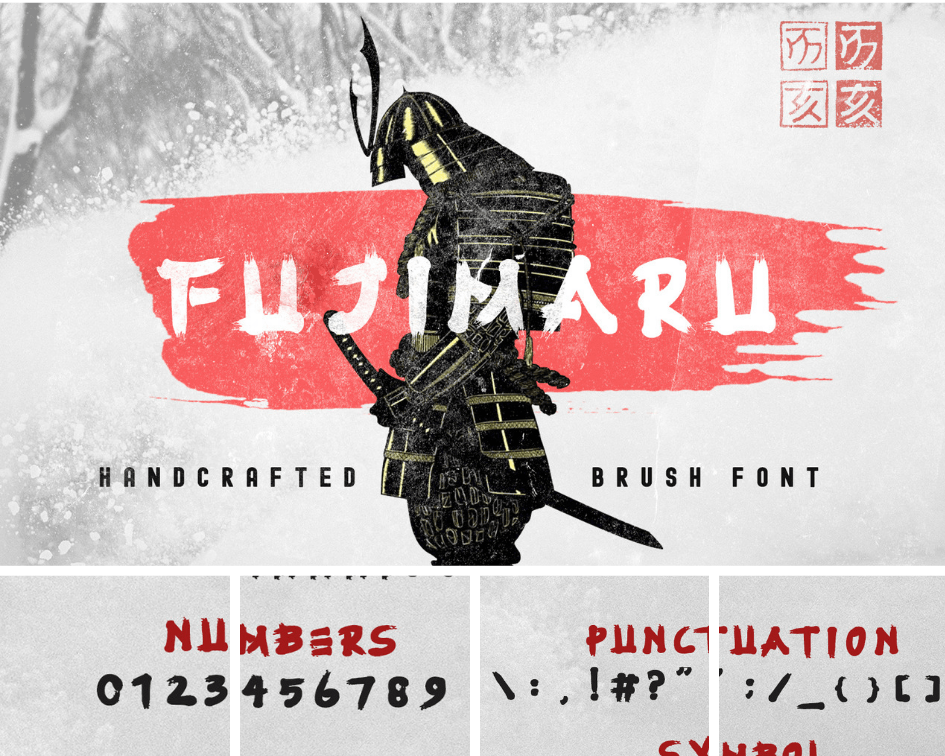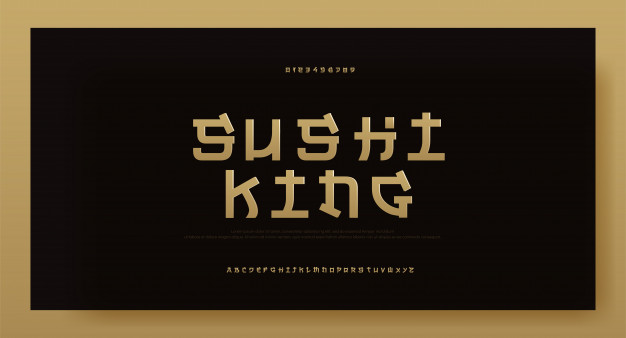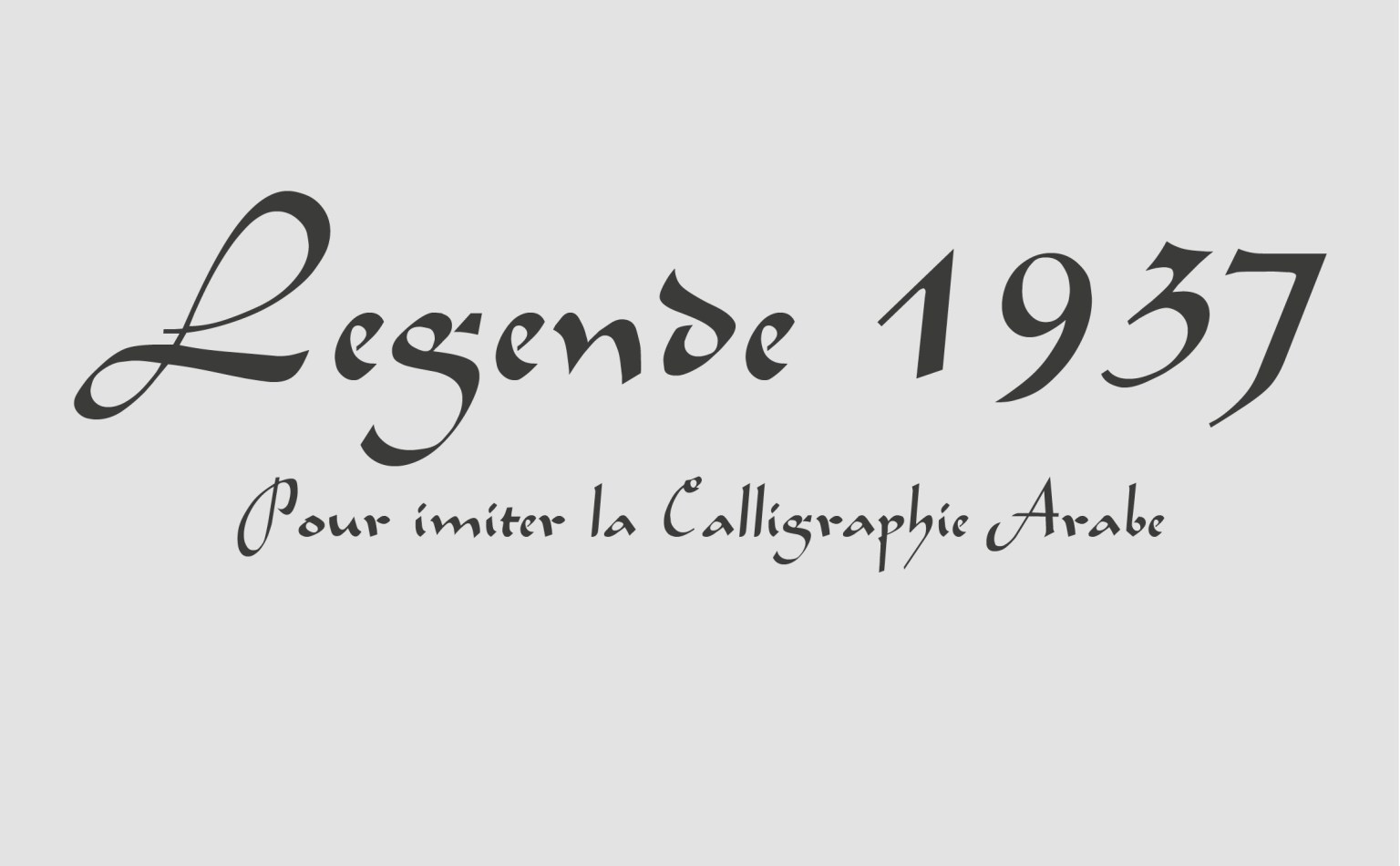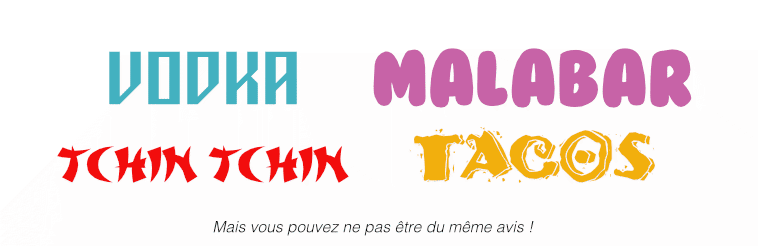
Typographie : comment éviter les stéréotypes ?
La typographie n’est pas exempte de stéréotypes.
Ainsi, certaines polices sont associées à un évènement historique marquant, d’autres font systématiquement référence à un pays ou à une culture. C’est ce que l’on appelle la stéréo typographie.
Alors comment éviter les stéréotypes quand on choisit une typographie ? Voici quelques pistes à explorer pour mieux comprendre la stéréo typographie et ainsi l’éviter.
Une police suscite nécessairement des émotions. Elle est utilisée pour appuyer le sens et le ressentie d’une conception graphique. Le pouvoir suggestif de la typographie est donc très important. Dans certains cas, ce pouvoir suggestif donne un sens culturel ou ethnique à une typographie.
Luxe, futurisme, guerre… nous associons nos choix de police à des concepts très variés. Dans ce cas, le stéréotype, bien que présent, n’est pas encore insultant. En revanche, de nombreuses polices sont automatiquement perçues comme exotiques.
Les connotations parfois racistes de ces polices se sont en réalité progressivement développées. Leurs apparitions répétées sur les affiches promotionnelles, les couvertures de livres, etc. les ont petit à petit intrinsèquement liés à un préjugé, renforçant leur connotation ethnique ou culturelle dans l’esprit du public.
Le stéréotype est un élément nécessaire à l’élaboration de l’identité sociale. Mais il s’agit aussi d’un schéma de pensée extrêmement simplificateur qu’il n’est pas toujours facile de dépasser. En effet, nous sommes tous sujets aux préjugés, même de manière inconsciente.
La grande majorité des typographiques assimilées à un pays ou à une culture est victime de stéréotypes depuis l’essor colonial de la civilisation occidentale. Ces polices sont souvent clairement marquées par le contexte raciste de cette époque qui réduit la culture complexe d’un pays à un simple trait culturel, de surcroît considéré comme primitif.
C’est durant cette période que les typographies aux accents asiatiques, arabes ou encore grecs… voient le jour.
L’une des plus marquées n’est autre que Neuland, considérée au début du XXe siècle comme une typographie rebut. Elle va alors copieusement alimenter les visuels afro-américains incontestablement racistes.
Dans les années 1940, elle continue d’être utilisée pour représenter la population noire, mais perd son caractère raciste pour celui de stéréotype.
Un autre exemple que vous ne manquerez pas de reconnaître, la police ChopsUey qui manque totalement de saveur et de nuance.
Cette typographie dite « asiatique », imite un ou deux petits coups de pinceau afin de former un alphabet qui est en fait bien loin de traduire les nuances et l’harmonie de la calligraphie.
Certaines polices ont également été marquées par l’histoire. Comment ne pas citer ici l’exemple des polices gothiques qui souffrent encore aujourd’hui de leur utilisation dans la propagande nazie. Dans les années 30 à 45, on les considère même comme un signe distinctif aryen.
Parmi les polices appréciées par le nazisme, s’en trouve une bien plus moderne : la Futura, qu’Hitler affectionnait tout particulièrement. Cette dernière ne souffre toutefois plus de son histoire, au contraire des polices gothiques toujours très fortement connotées.
Attaqués par les minorités visées, certains produits sont retirés du marché pour leur connotation.